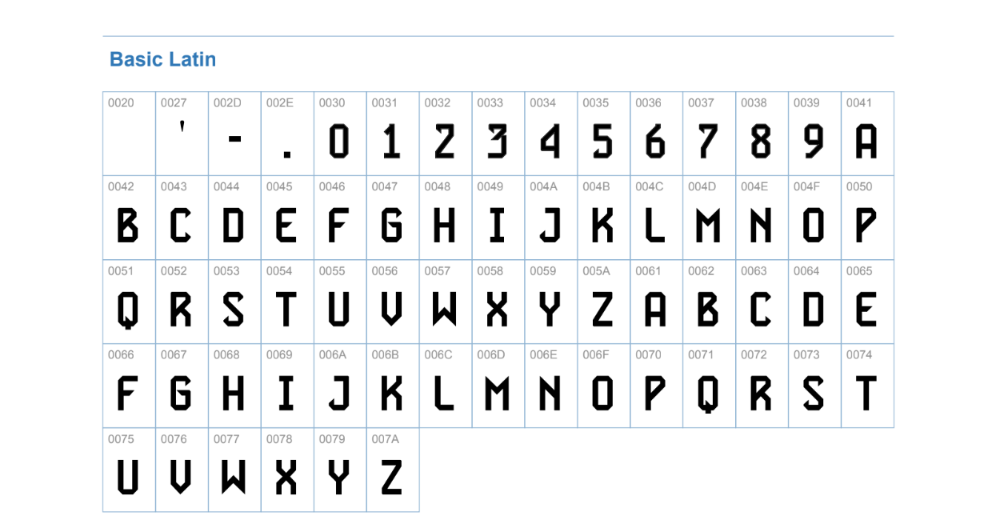
O Bayern de Munique acaba de apresentar sua identidade visual para a temporada 2026-2027. E, como de costume, a nova fonte oficial já virou assunto entre torcedores e designers.
A tipografia entra em campo pela primeira vez na pré-temporada. Promete unir tradição bávara com um toque moderno e agressivo, bem ao estilo do time.
Estilo visual da tipografia
Os números ganharam ângulos retos e serifas geométricas. Algo raro no futebol atual.
Os caracteres têm espessura uniforme, garantindo leitura rápida até em drones de transmissão. A inspiração vem da arquitetura de Munique: precisa, robusta e imponente.
Aplicação no uniforme
Home (titular): Números em branco com contorno vermelho escuro, sobre o miolo tradicional rubro.
Away (reserva): Fonte preta sólida, sem contornos, na camisa clara.
Third (terceiro): Versão dourada metálica, exclusiva para jogos europeus.